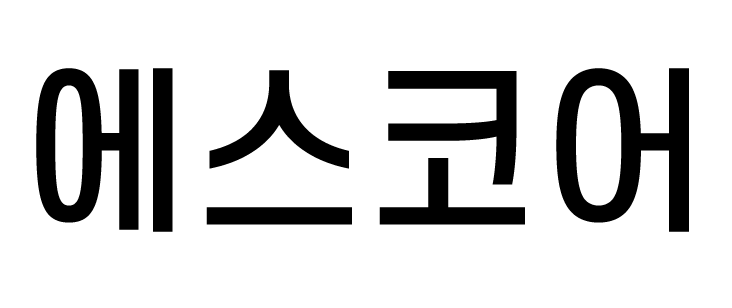
에스코어 드림
ExtraLight
ExtraBold
Heavy
에스코어 드림은 ‘Dream(꿈)’과 ‘드리다’라는 두 가지 뜻을 가지고 있습니다. 꽉 찬 직사각형 구조의 제목용 글꼴로써 복고적인 형태에 현대적인 감성을 담았습니다. 각 자소에서 보여지는 수직적인 획의 마감은 전체적인 구조와 어우러져 새로운 글꼴의 표정을 제시합니다.
- Sans,민부리
- 에스코어 드림 / S-CoreDream